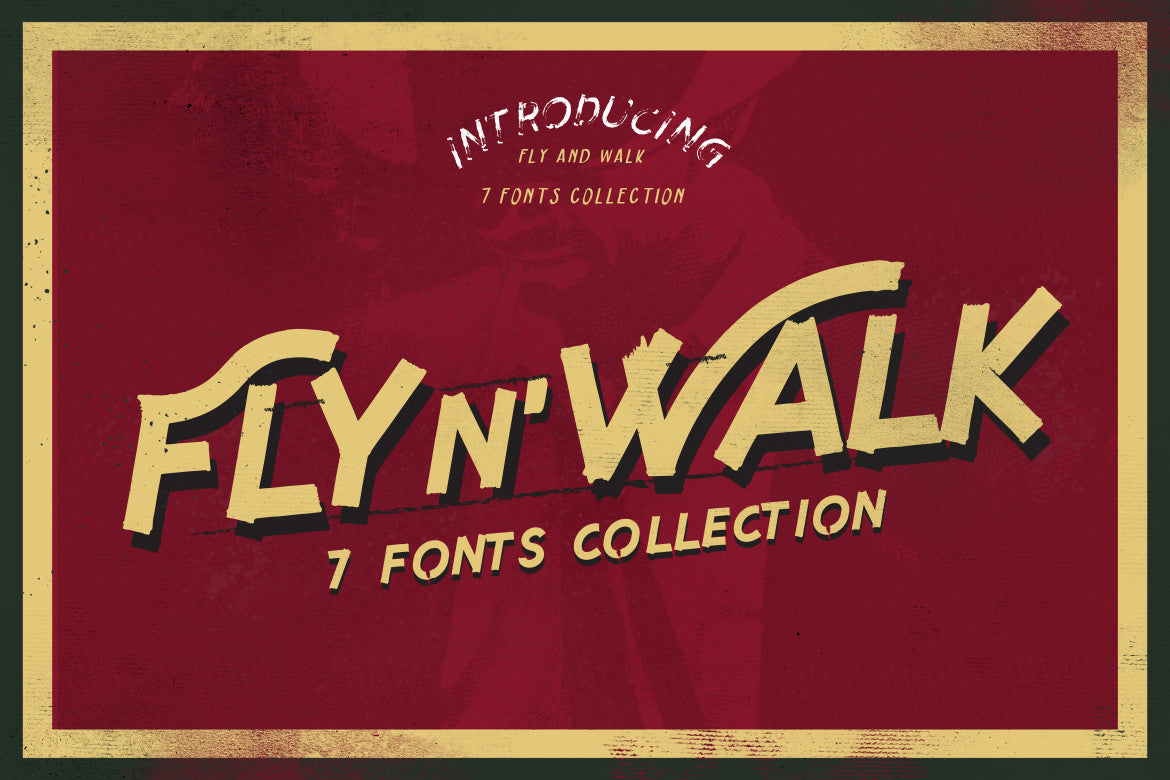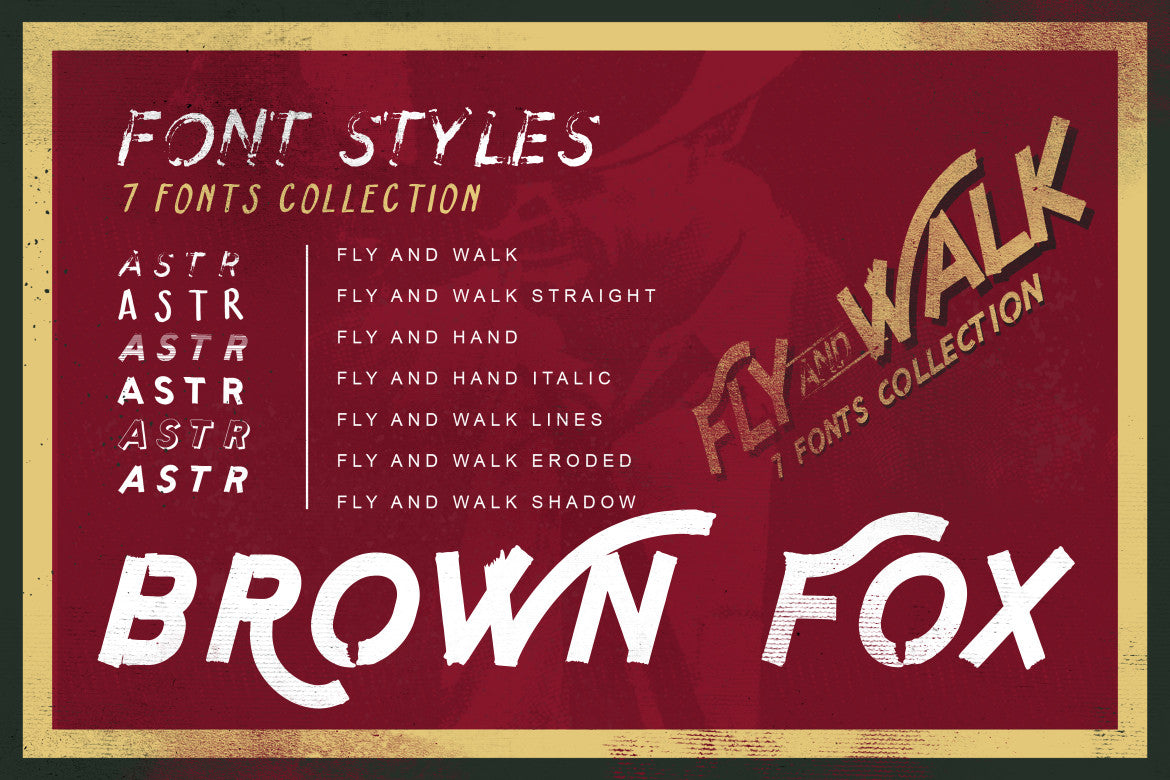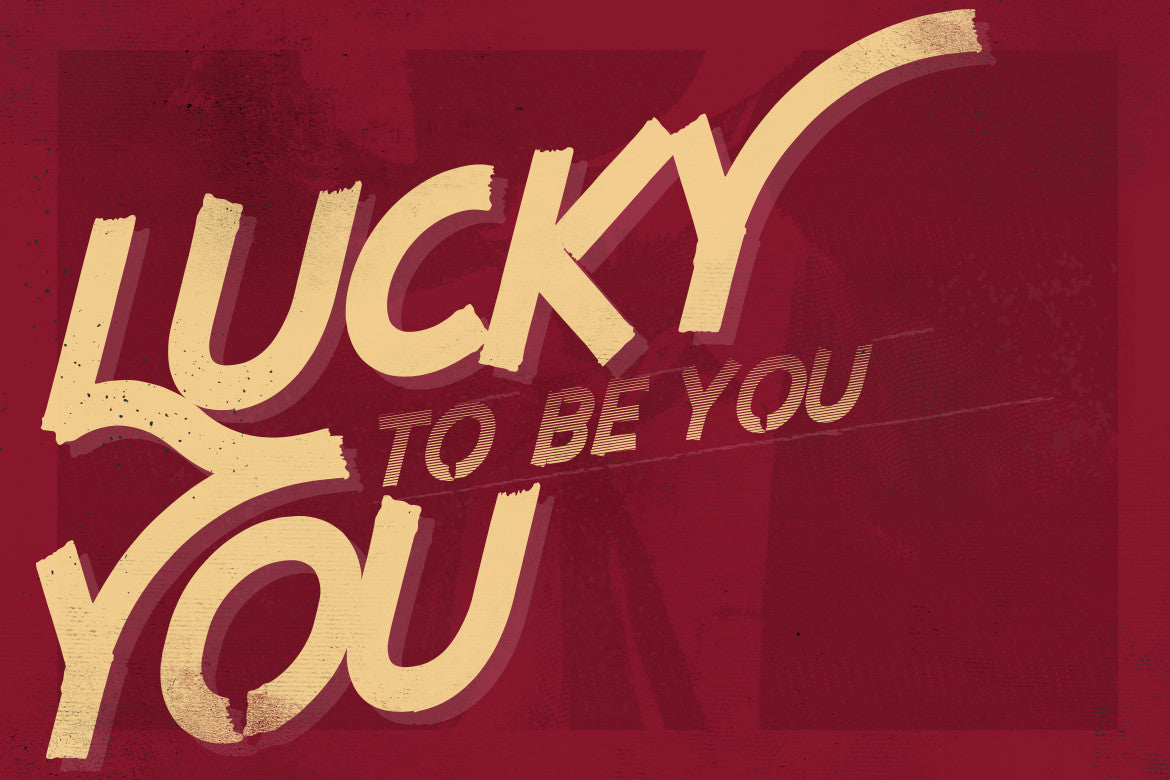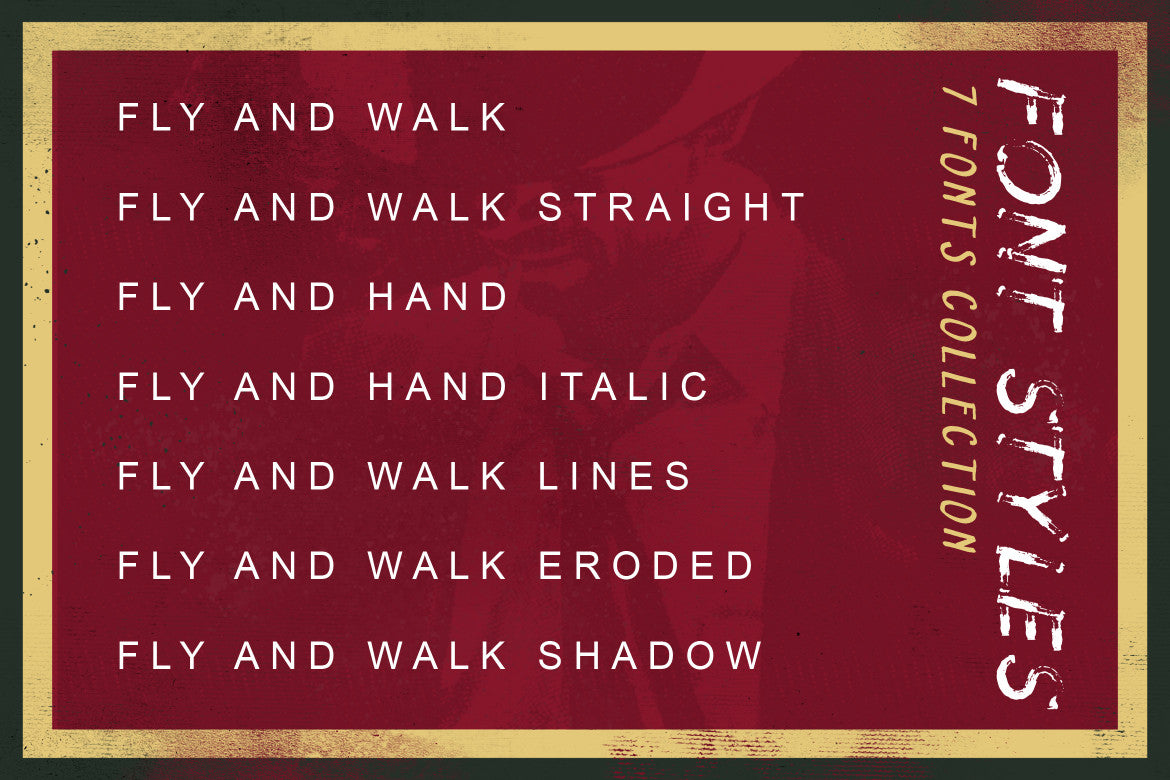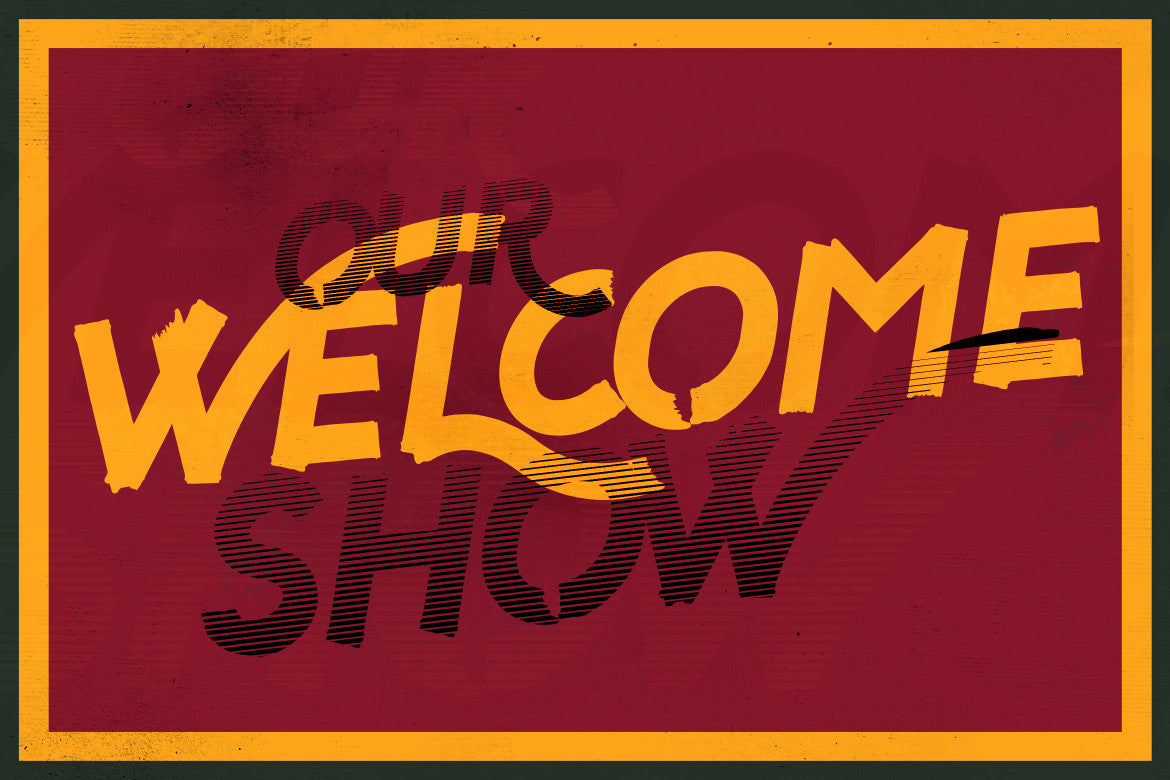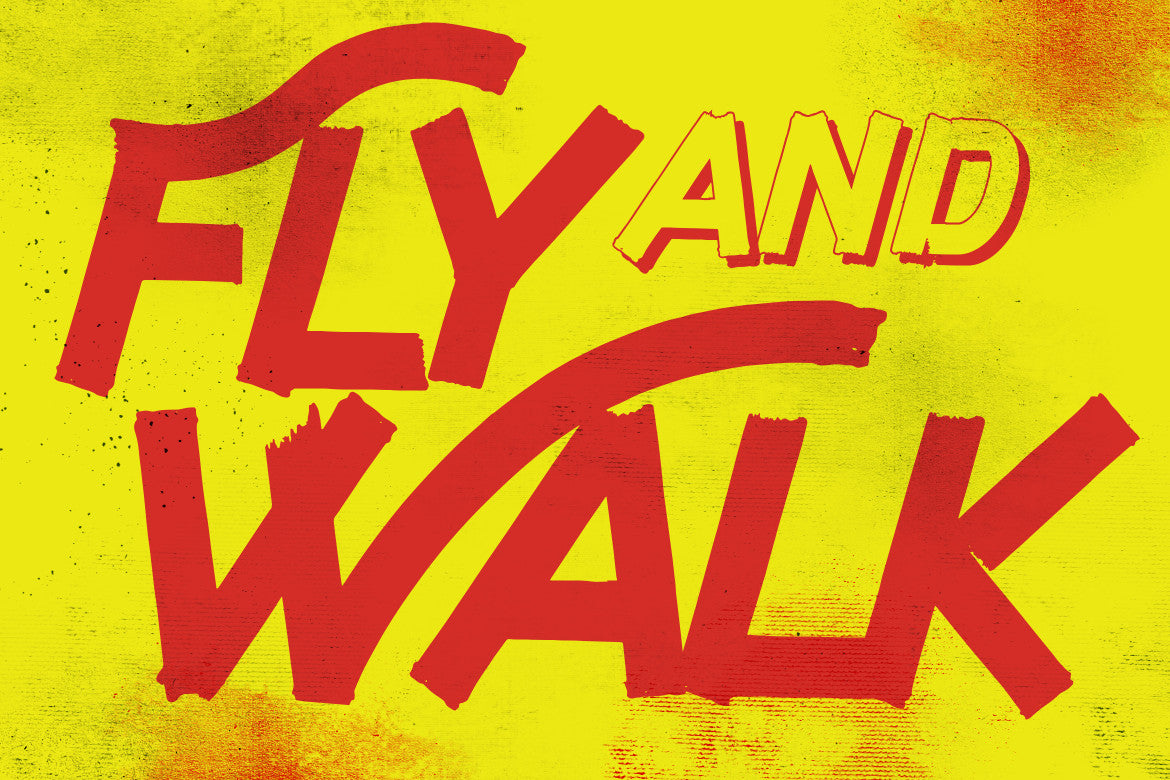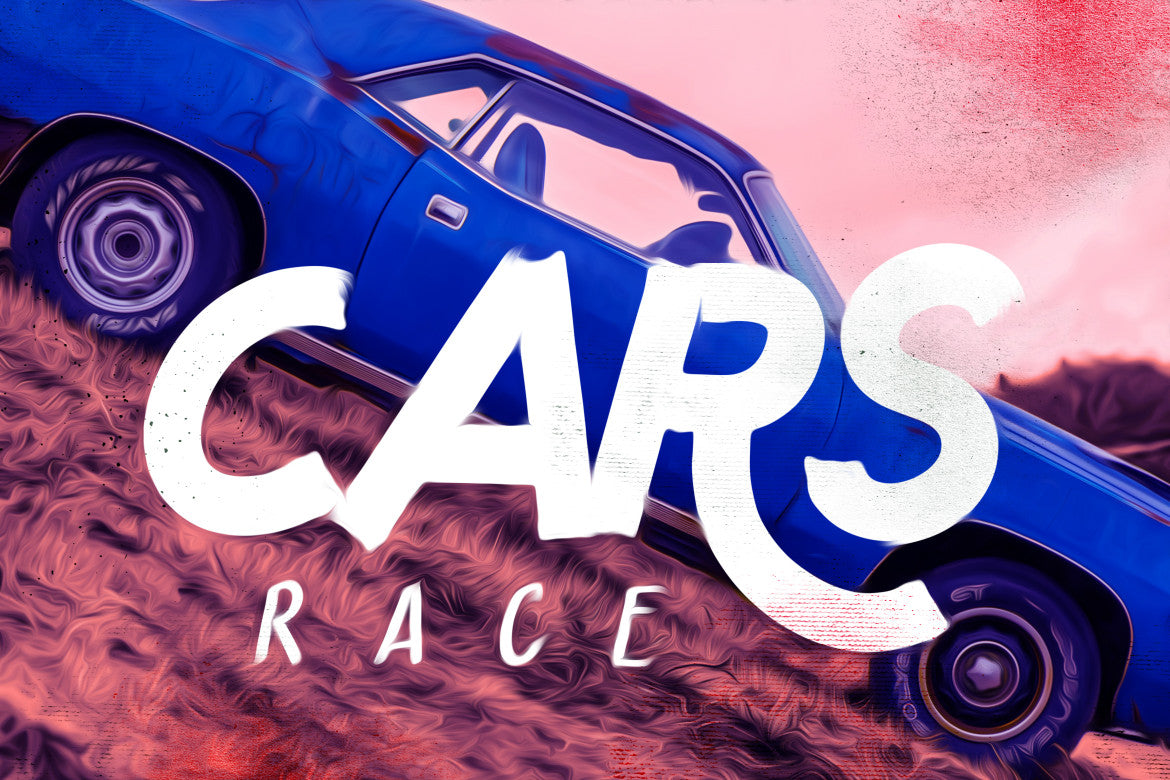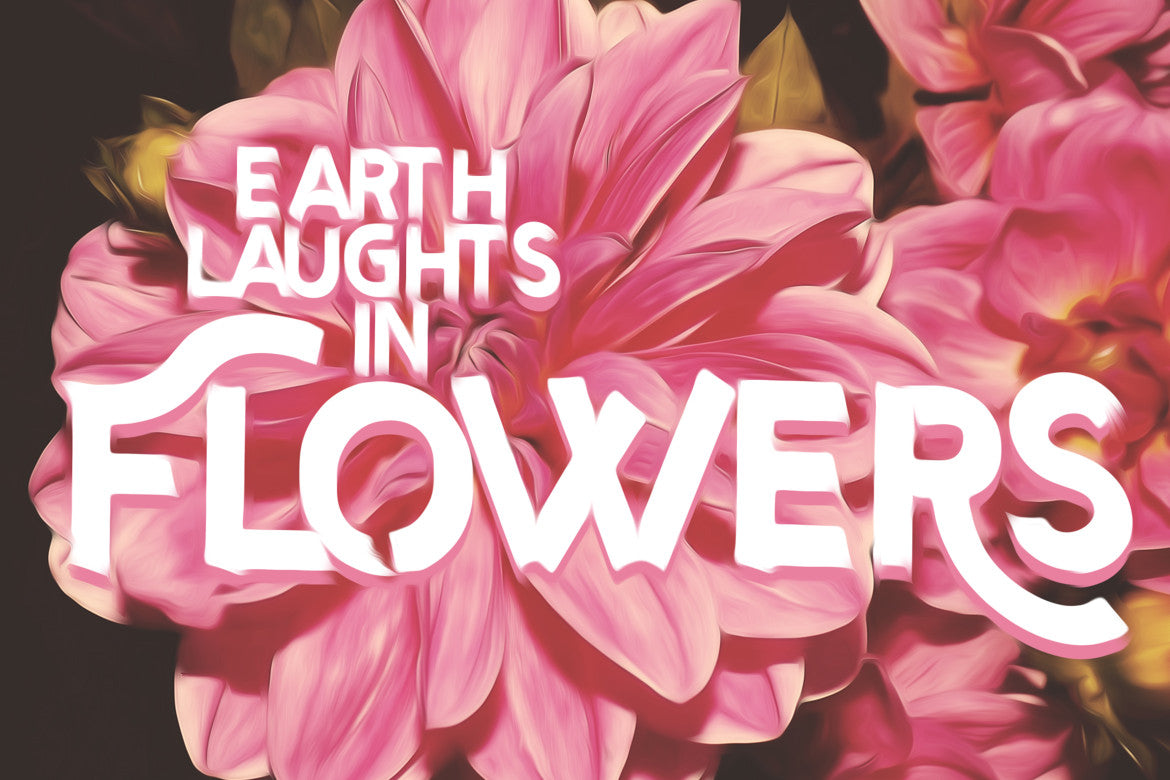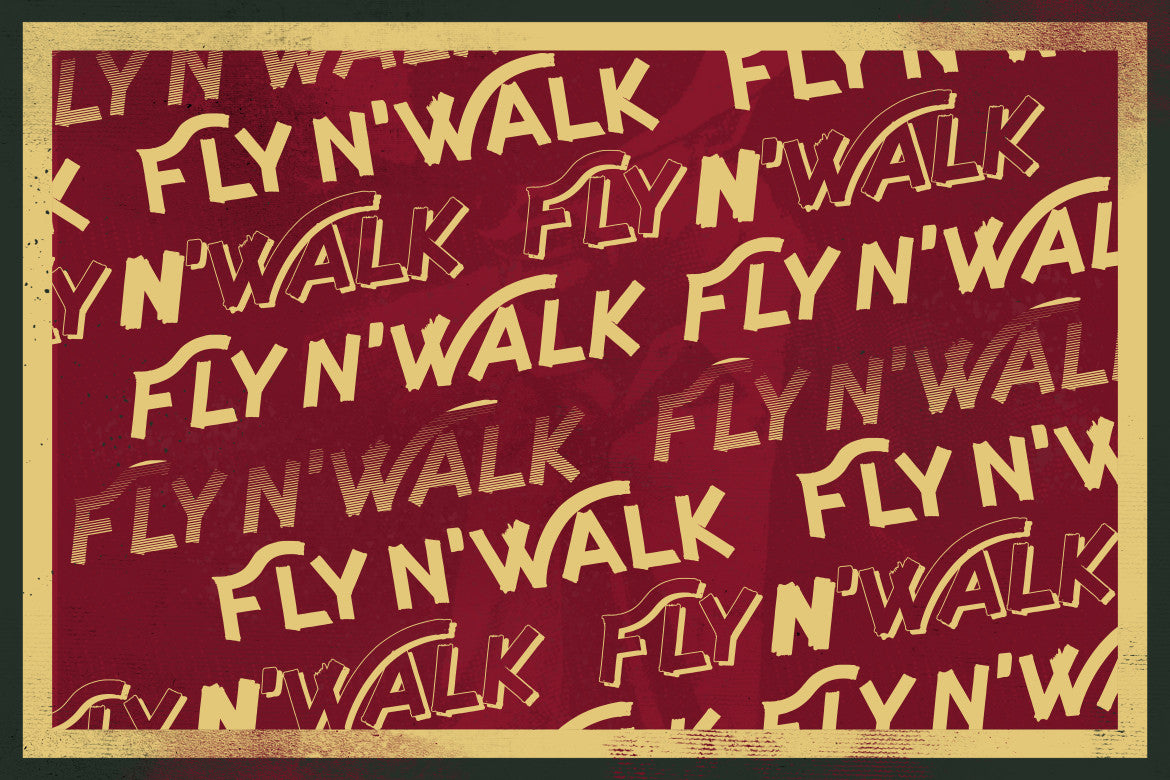
フライアンドウォーク書体
Fly and Walk 書体ソーシャル メディアのプレゼンテーション、ロゴ、ブランディング、その他のクリエイティブで楽しいプロジェクトに最適なソリッド フェイスで、セットを自分のスタイルに合わせて簡単にカスタマイズできます。
素晴らしいディスプレイ、ラベル、衣類、映画シーン、ポスター、映画のタイトル、ライブ、アルバムカバー、ロゴなどに使用できます。
ビンテージ バイクのカスタム カルチャーからインスピレーションを得た手作りのサンセリフ (すべて大文字)。
フォントには 7 つのスタイルがあり、クリアなデザインからラフなデザインまで、レトロやビンテージのプロジェクトに最適です。
7 つの異なるスタイルのフォントのコレクション。
- 飛んで歩く
- まっすぐに飛んで歩く
- フライアンドハンド
- フライアンドハンドイタリック
- フライ&ウォークライン
- 飛ぶことも歩くことも侵食される
- 飛んで歩く影